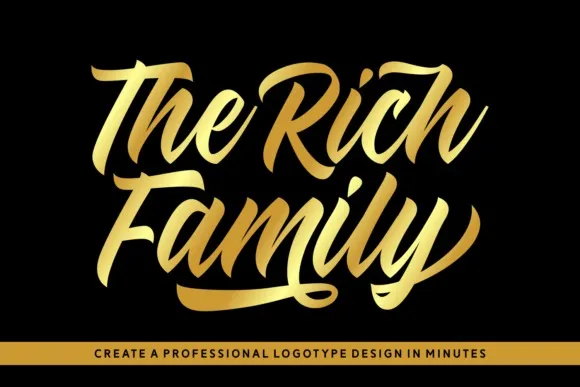
The Rich Family Font – Download Grátis
A fonte ‘The Rich Family Font’ é uma elegante escolha para aqueles que desejam adicionar personalidade ao seu design. Feita pelo designer Keithzo (7NTypes), essa fonte caiada tem um tom delicado e fluido, excelente para diversas aplicações como logomarcas, convites de casamento, cabeçalhos, camisetas, banners do YouTube, e muito mais. O fato de ser PUA encoded permite que você acesse todos os gílitos e cintilantes facilmente. Seja você um designer gráfico ou uma empresa propondo design para eventos especiais, certamente vai apreciar o poder desta fonte. Seu estilo elegante torna-o perfeito para estilos modernos ou românticos, dependendo do uso que você desejar dar a ela. Com ‘The Rich Family Font’, transforme sua arte digital de maneira única e elegante. É um recurso gráfico indispensável para qualquer designer em busca de uma fonte profissional que destaca-se no mercado.